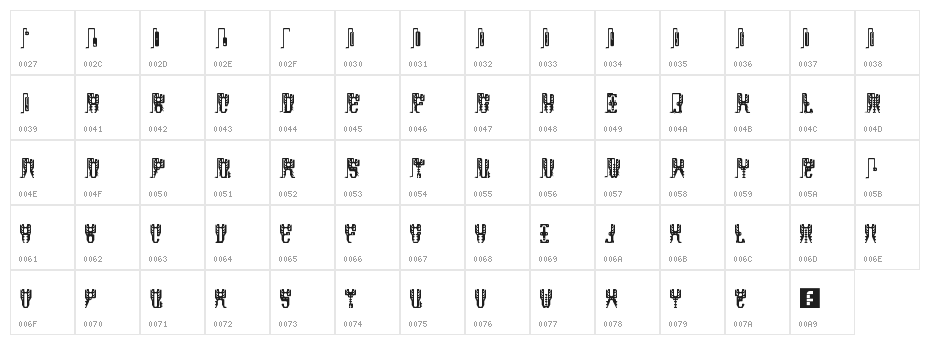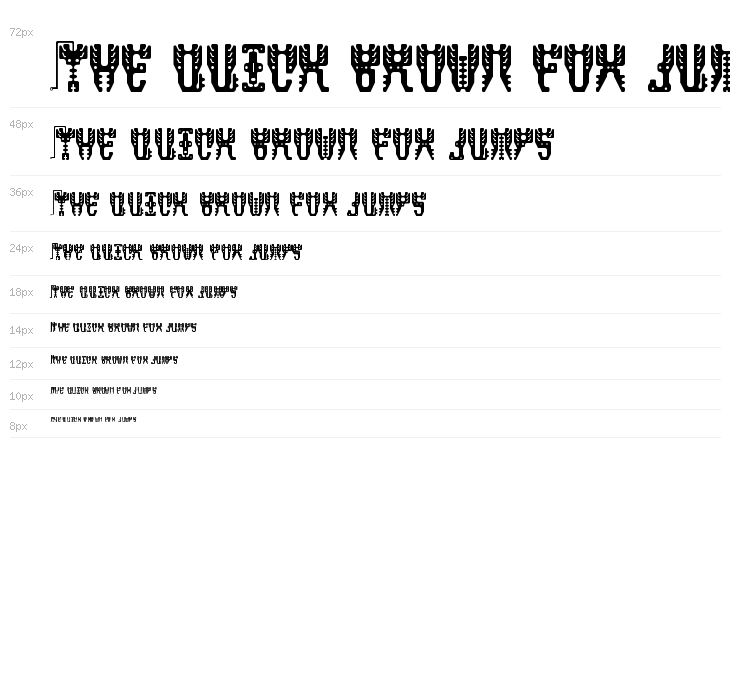
masquerade Regular Font
| Vorgeschlagene Projekte | Ideal for theatrical posters, event invitations, book covers, and branding that requires a touch of elegance and drama. |